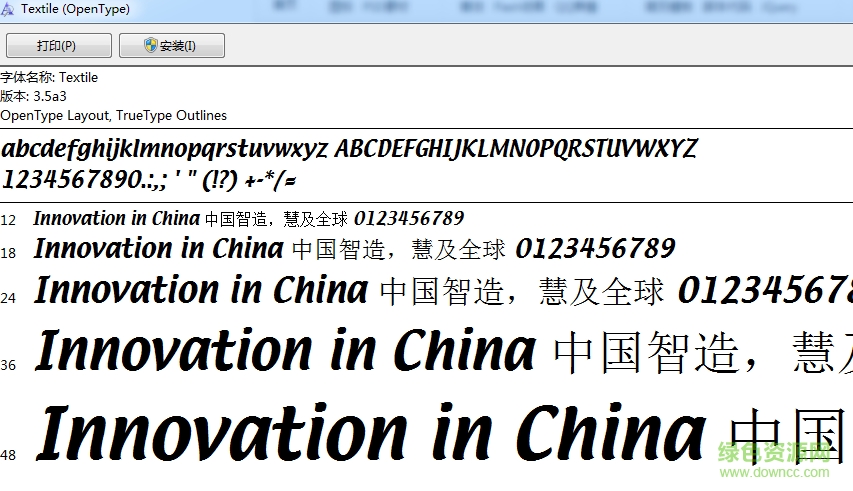
TextileRegular字體是英文字體庫(kù)中的個(gè)性字體,字體非常飄逸具有個(gè)性,線條的不規(guī)則性給用戶帶來(lái)了更好的視覺(jué)體驗(yàn),喜歡的朋友就來(lái)綠色資源網(wǎng)下載使用吧!
TextileRegular字體是一款個(gè)性英文字體,字體非常適合用于平面設(shè)計(jì)行業(yè),有需要的朋友就趕快來(lái)綠色資源網(wǎng)下載吧!